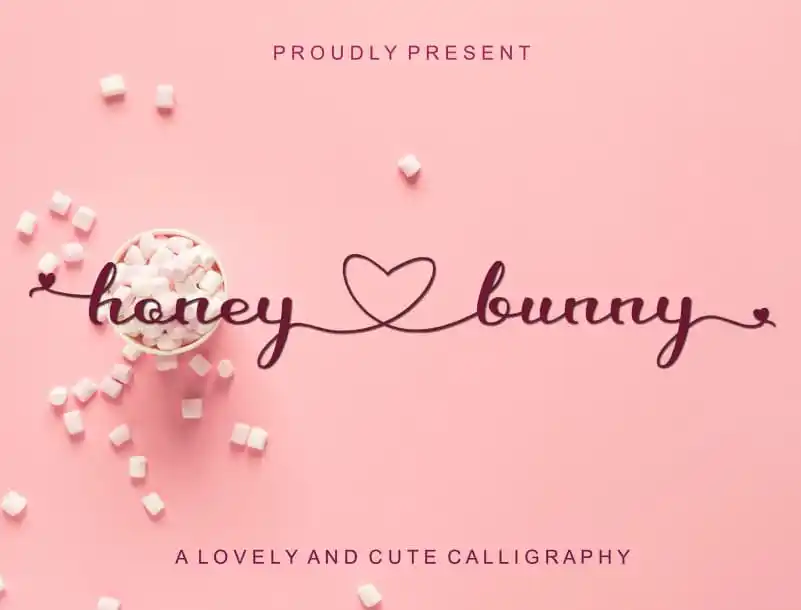
Honey Love Bunny Calligraphy Font – Fonte Grátis
Honey Love Bunny Calligraphy Font
A Honey Love Bunny é uma fonte de tipografia calligrafia moderna criada pelo designer Ahmad Afandi. Ideal para uma ampla variedade de projetos, esta fonte oferece um toque elegante e divertido que vai fazer a diferença tanto no branding quanto nas criações exclusivas. Desde estilos de marca e logos até designs para festas de casamento, posts da mídia social, anúncios, embalagens, roupas personalizadas, produtos finos, etiquetas, fotografias e até mesmo sobreposições e convites, a Honey Love Bunny é uma opção versátil que combina sofisticação com um toque de descontração. Seja você criando seu próprio produto ou trabalhando para alguém mais, esta fonte vai garantir que cada detalhe seja encantador e impecavelmente bem-formatado. Experimente a Honey Love Bunny e encontre o design perfeito para seus projetos.